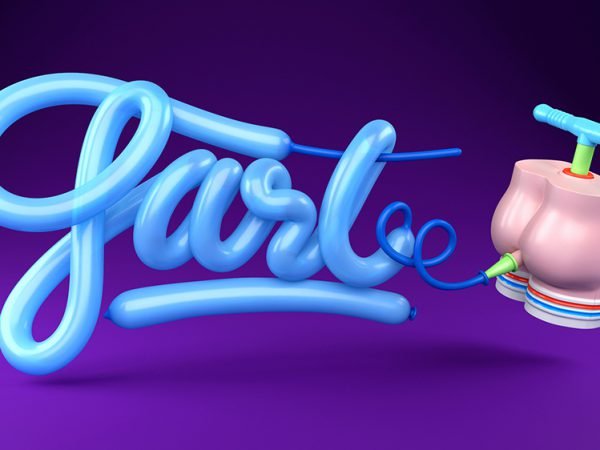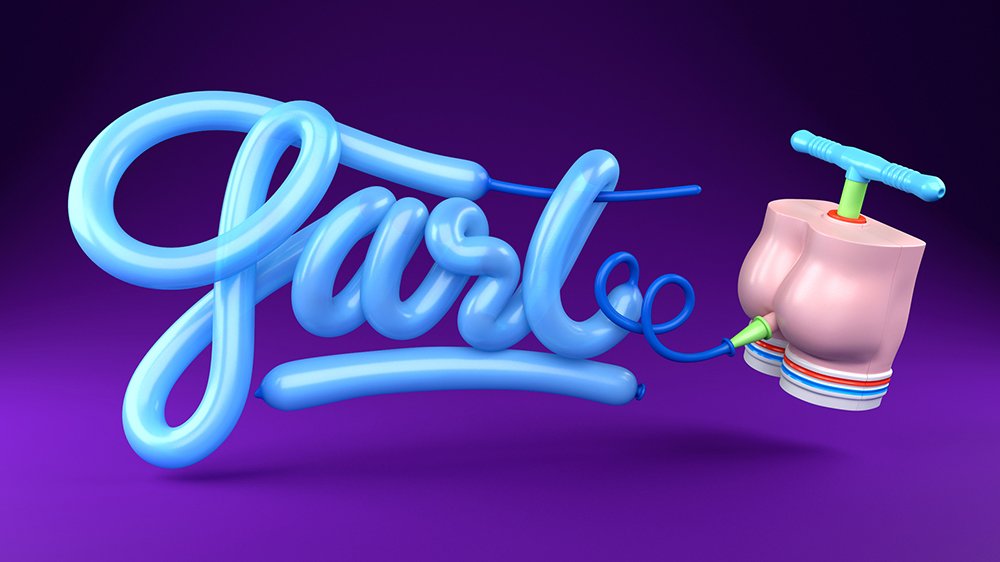
Ilustración digital 3D: las series tipográficas Muokkaa
Alejandro López Becerro es el diseñador detrás de Muokkaa, el alias bajo el cual reúne una variada colección de series tipográficas. Especializado en ilustración 3D, el creativo nacido en Salamanca estudió diseño gráfico en la Escuela de Arte de la ciudad.